정보가 넘쳐나는 시대에는 뉴스가 ‘무슨 내용을 다루느냐’뿐 아니라 ‘어떻게 보여 주느냐’도 똑같이 중요합니다. 화면이 종이를 대신하고, 알고리즘이 콘텐츠 유통을 좌우하는 지금도 사람들은 여전히 폰트나 레이아웃, 시각적 톤을 보고 그 매체가 신뢰할 만한지, 전문적인지, 믿을 수 있는지를 직감적으로 판단합니다.
이 글에서는 유럽·미국의 전통 언론부터 새롭게 떠오른 디지털 미디어까지, 세계 주요 뉴스·미디어 브랜드들이 어떤 폰트와 시각 전략을 사용하고 있는지 살펴봅니다. 글자 모양과 행간처럼 작은 디테일이 뉴스에 담긴 권위와 온기를 어떻게 은근하게 만들어 내는지도 함께 짚어보겠습니다.
뉴욕 타임스
THE NEW YORK TIMES
Font: ITC Franklin Gothic + Cheltenham
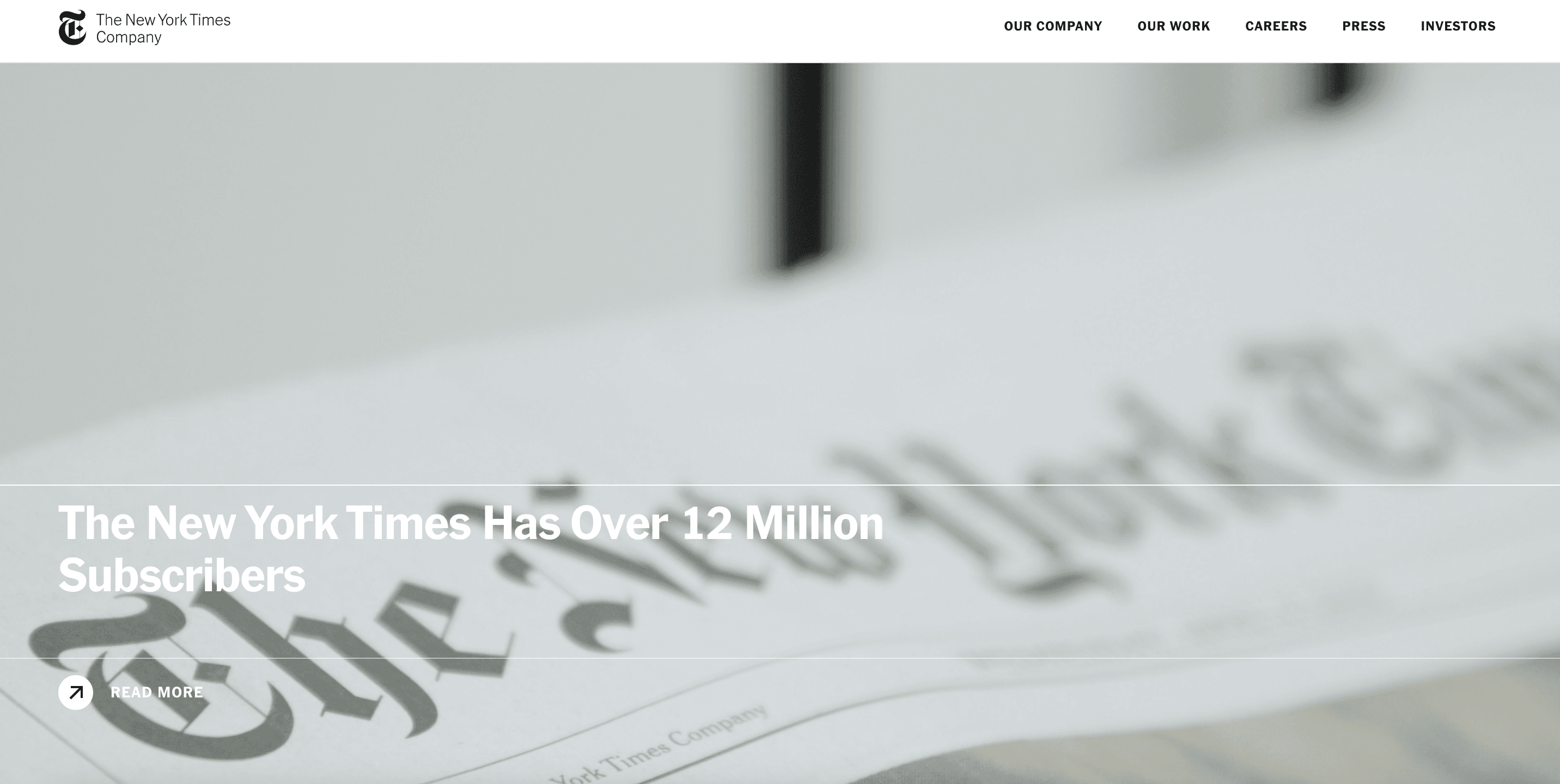
The New York Times Company(뉴욕 타임스 컴퍼니)는 1851년에 설립된 미국의 대표적 뉴스 기관으로, 깊이 있는 보도와 엄격한 저널리즘으로 잘 알려져 있습니다. 이 브랜드의 핵심 폰트 시스템은 Franklin Gothic과 Cheltenham입니다.
그중에서도 Franklin Gothic은 현대적이고 이성적인 느낌이 강한 서체로, 제목과 내비게이션, 다양한 디지털 인터페이스에 폭넓게 쓰입니다. 또렷한 형태 덕분에 단단하고 신뢰감 있는 시각적 이미지를 만들어 주며, 뉴욕타임스 브랜드의 전문성을 안정적으로 뒷받침합니다.
Cheltenham은 대비가 뚜렷한 세리프 구조와 조금 촘촘한 리듬감 덕분에 브랜드에 더 엄숙하고 전통적인 분위기를 더해 줍니다. 이 서체가 들어가면 전체적인 인상이 한층 단단해지고, 뉴스 매체가 지닌 특유의 힘과 역사적 깊이가 자연스럽게 드러납니다.
디지털 환경으로 무게중심이 옮겨간 지금도 뉴욕 타임스는 이 고전적인 서체 조합을 기본으로 유지합니다. 대신 더 가벼운 굵기와 넉넉한 여백을 적극 활용해 표현 방식을 현대적으로 조정하고 있습니다. 덕분에 오랜 시간 쌓아 온 브랜드 신뢰도는 그대로 지키면서도, 보다 명료하고 이성적인 시각 언어를 동시에 구현하고 있습니다.
블룸버그
BLOOMBERG
Font: Neue Haas Grotesk
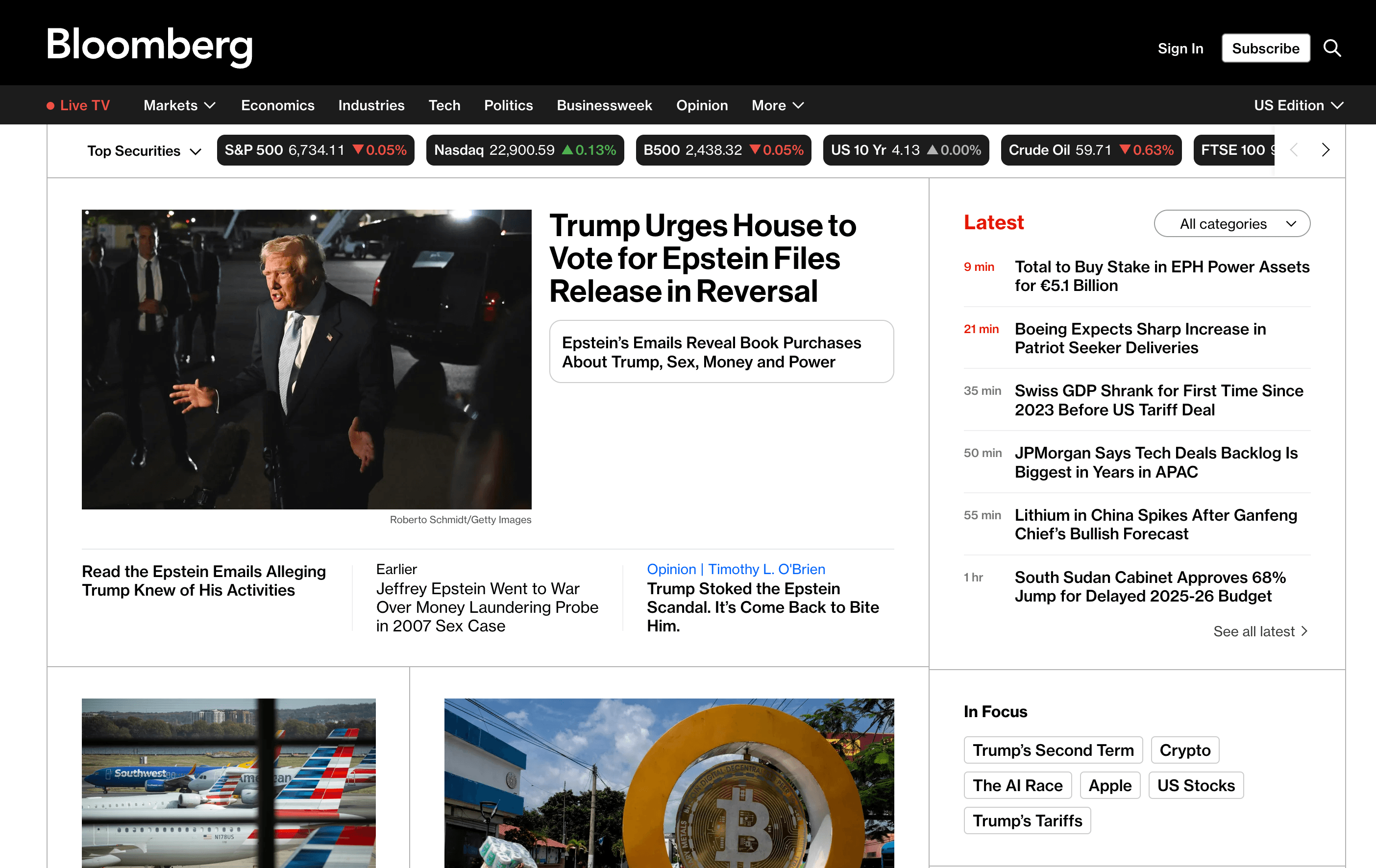
블룸버그는 세계에서 가장 영향력 있는 금융·비즈니스 정보 기관 가운데 하나로, 시각적 아이덴티티의 핵심 서체로 Neue Haas Grotesk를 사용합니다.
스위스 전통에서 출발한 이 산세리프 서체는 명료하고 엄격한 구조와 중립적인 기하학적 형태가 강점입니다. 덕분에 빽빽한 데이터, 차트, 금융 정보가 쏟아지는 환경에서도 높은 가독성과 전문성을 안정적으로 유지해 줍니다.
블룸버그의 디지털 플랫폼과 단말기 인터페이스, 브랜드 커뮤니케이션 전반에서 Neue Haas Grotesk는 균형 잡힌 굵기 체계와 군더더기 없는 글자 형태를 통해 차분하고 이성적이며 data-driven(데이터 드리븐)한 브랜드 이미지를 만듭니다. 기능성을 최우선에 두면서도 글로벌 금융 미디어로서의 효율성과 권위를 함께 강화하는 선택입니다.
워싱턴 포스트
THE WASHINGTON POST
Font: 커스텀 서체 Postoni + Franklin Gothic
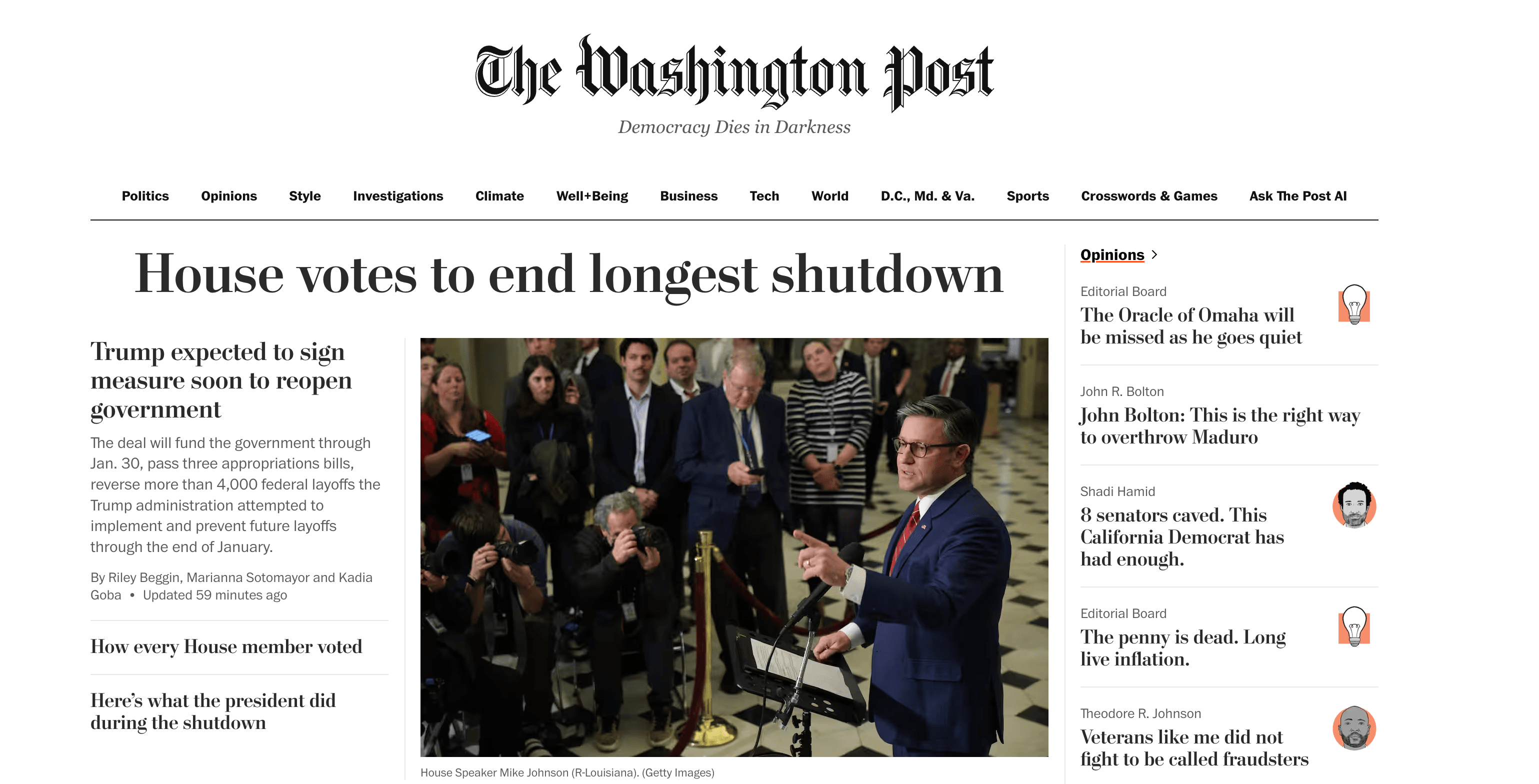
The Washington Post(워싱턴 포스트)는 1877년에 창간된 미국의 대표 일간지로, 심층 탐사보도와 정치 보도로 명성이 높습니다. 이 매체의 시각적 아이덴티티는 Postoni와 Franklin Gothic을 중심으로 구성되어 있습니다.
Postoni는 워싱턴 포스트를 위해 특별 제작된 세리프 서체로, 전설적인 서체 디자이너 Matthew Carter(매튜 카터)가 Bodoni의 고전적 구조를 현대적으로 재해석해 완성한 서체입니다. 헤드라인에서 우아한 권위와 묵직한 역사성을 드러내며, 신문의 정체성을 상징하는 핵심 요소로 작동합니다.
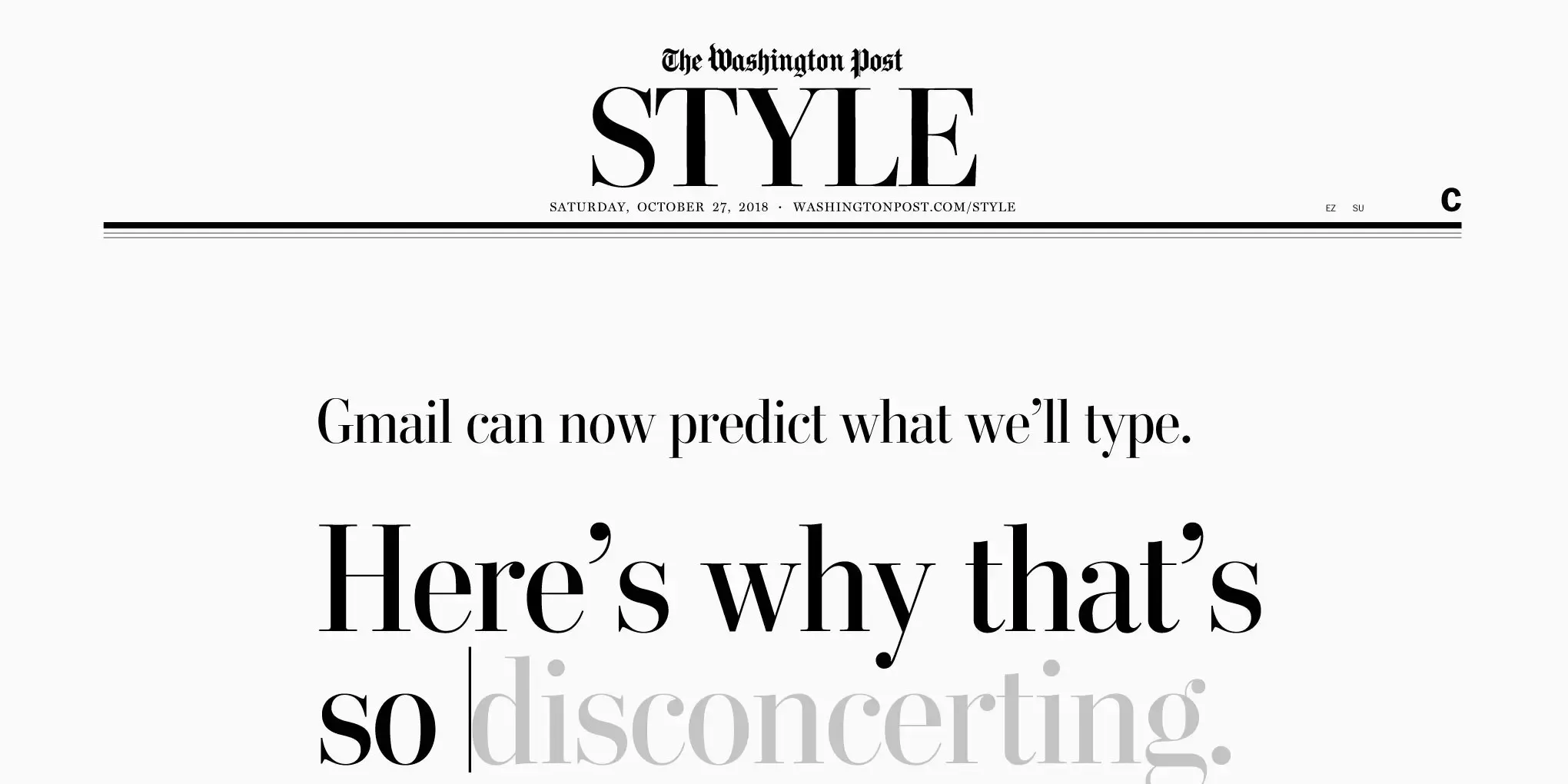
이에 반해 Franklin Gothic은 현대 뉴스 매체가 요구하는 명료함과 전문성을 더해 주고, 전체 시각 흐름에 선명한 리듬을 만들어 줍니다.
두 서체의 조합은 전통 신문이 가진 엄숙함을 유지하면서도, 디지털 시대에 맞는 이성적 긴장감과 역동성을 함께 보여 줍니다. 역사적 유산과 동시대적 감각을 자연스럽게 아우르는 시각 언어라고 할 수 있습니다.
POLITICO
Font: DIN + Helvetica Neue
POLITICO는 2007년에 설립된 워싱턴 D.C. 기반의 정치 뉴스 미디어로, 미국과 유럽의 정치 보도, 정책 분석, 선거 관련 뉴스를 중심으로 다루는 매체입니다.
브랜드의 시각적 아이덴티티는 DIN과 Helvetica Neue를 중심으로 구성됩니다. DIN은 기하학적 비례와 넓은 자형, 뛰어난 가독성을 강점으로 삼아 대제목에 주로 사용되며, 현대적이면서도 전문적인 인상을 줍니다. 반면 Helvetica Neue는 내비게이션과 본문에 활용되며, 간결하고 중립적인 특성 덕분에 전체 콘텐츠의 가독성과 일관성을 높여 줍니다.
이 두 서체의 조합을 통해 POLITICO는 디지털과 인쇄 환경 모두에서 이성적이고 권위 있으면서도 현대적인 뉴스 브랜드 이미지를 안정적으로 유지하고 있습니다.
BuzzFeed
BUZZFEED
Font: Proxima Nova
BuzzFeed는 2006년에 뉴욕에서 설립된 글로벌 뉴스·엔터테인먼트 미디어로, 디지털 콘텐츠 제작과 소셜 미디어 확산에 강점을 지닌 대표적인 인터넷 네이티브 매체입니다. 뉴스 보도와 트렌드 이슈, 인터랙티브 콘텐츠를 핵심으로 성장하며, 온라인 환경에서 자란 세대를 상징하는 브랜드로 자리 잡았습니다.
BuzzFeed의 시각적 아이덴티티에서 Proxima Nova는 핵심 서체로 사용됩니다. 서체 디자이너 Mark Simonson(마크 사이먼슨)이 디자인한 이 산세리프 서체는 기하학적 구조가 주는 이성적 느낌과 인문주의 서체 특유의 부드러운 감성을 함께 갖추고 있어, 현대적이면서도 친근한 인상을 전달합니다.
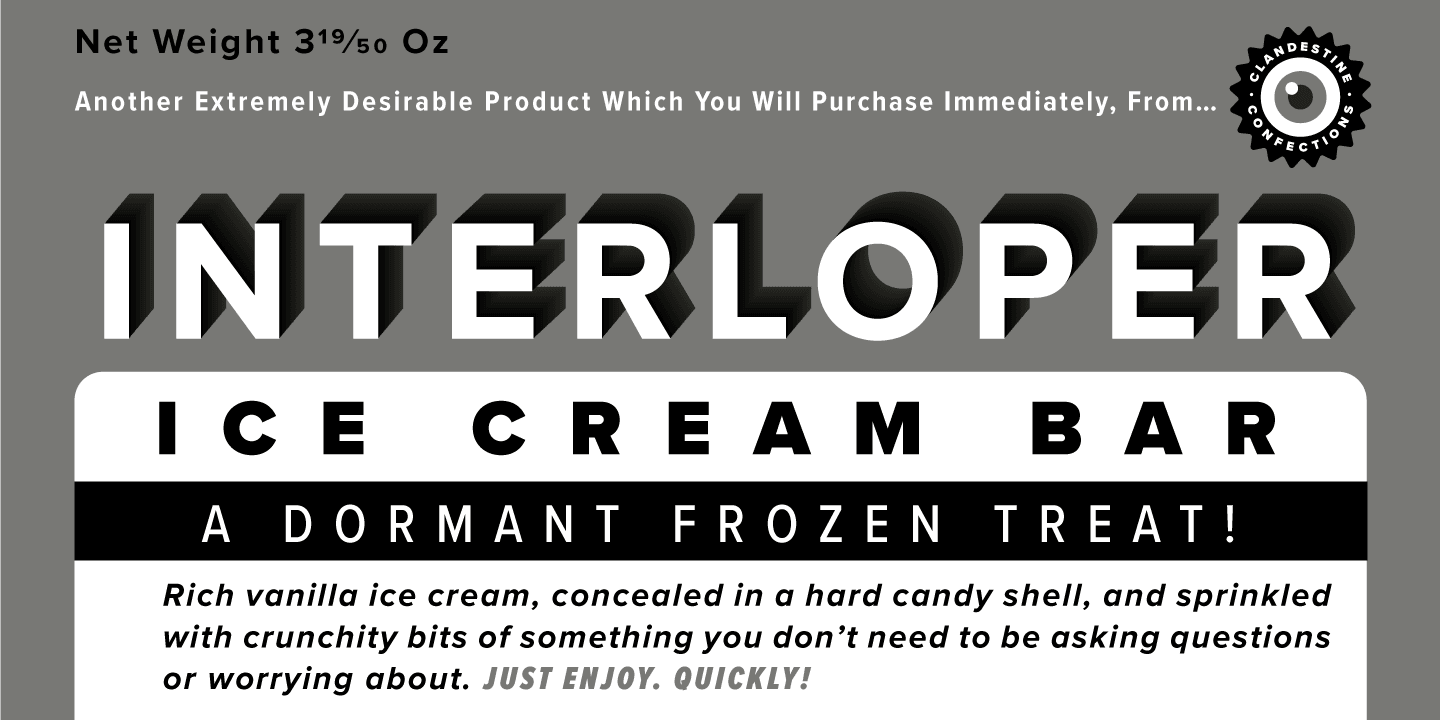
둥근 획과 균형 잡힌 자간 덕분에 Proxima Nova는 BuzzFeed 인터페이스를 가볍고 개방적이며 편안하게 보이도록 만듭니다. 이는 BuzzFeed가 지향하는 ‘디지털 네이티브, 즉각적인 콘텐츠, 빠르게 확산되는 커뮤니케이션’이라는 브랜드 성격과 자연스럽게 맞아떨어집니다.
타임스
THE TIMES
Font: Times New Roman 기반 커스텀 서체
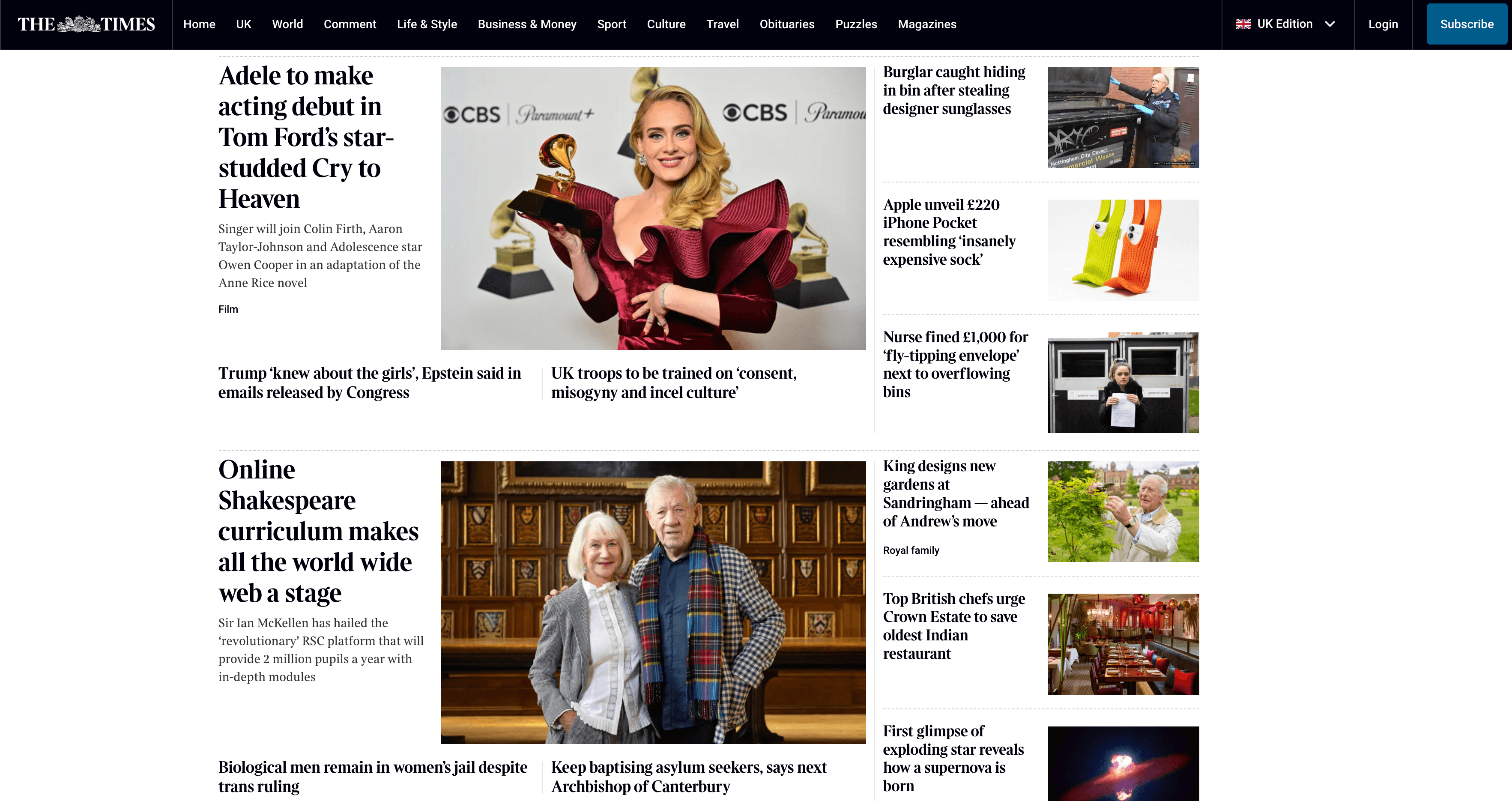
The Times(타임스)는 1785년에 창간된 영국의 대표 전국지로, 깊이 있는 보도와 권위 있는 논평, 전통적인 영국적 기풍으로 잘 알려져 있습니다.
브랜드 폰트 시스템은 클래식 서체 Times New Roman을 수정한 커스텀 서체 Times Modern을 중심으로 구성됩니다. 원본이 주는 책면 같은 묵직한 느낌과 달리, Times Modern은 더 가는 획 대비와 높은 명암, 넓어진 글자 폭을 통해 인쇄와 디지털 환경 모두에서 한층 가볍고 선명한 읽기 경험을 제공합니다.
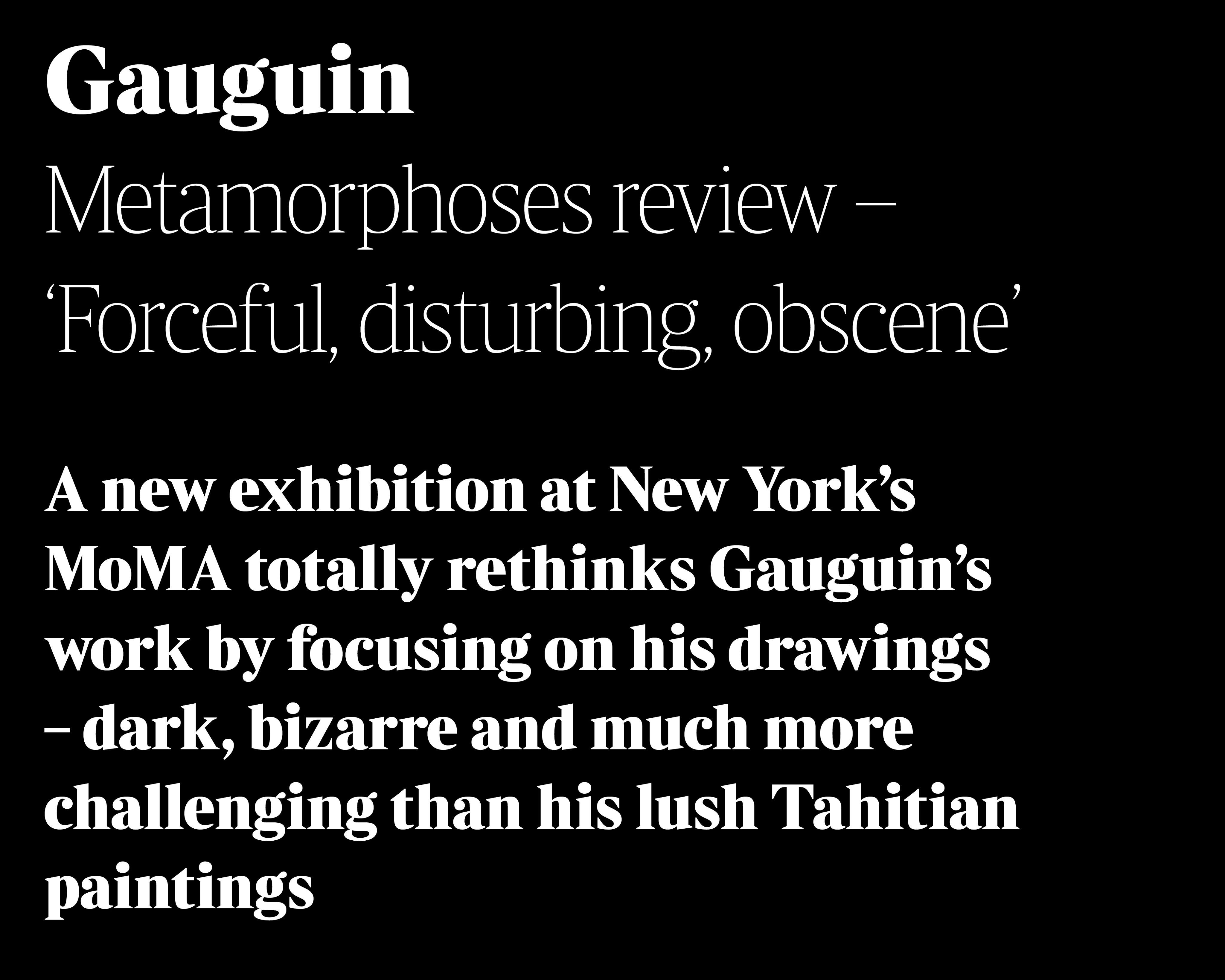
기존 서체를 현대적으로 다듬은 이 최적화 작업 덕분에 타임스는 영국식 신문 특유의 우아함을 유지하면서도 더 날렵하고 현재적인 표현을 구현합니다. 그 결과 디지털 시대에도 변함없는 중후함과 높은 인지성을 안정적으로 이어가고 있습니다.
허스트 매거진(그룹)
HEARST MAGAZINES
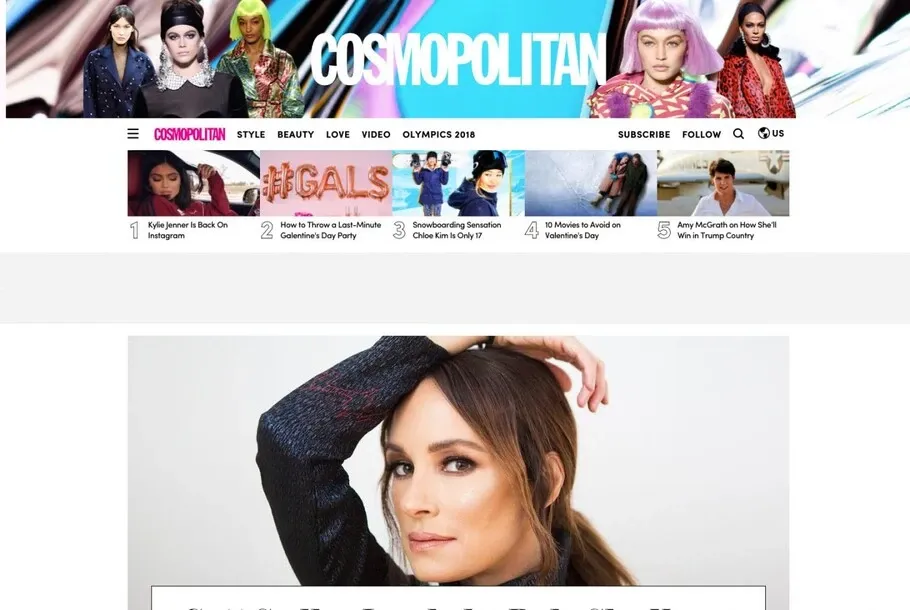
허스트 매거진 그룹은 지난 10여 년 동안 디지털 환경에 빠르게 적응해 왔습니다. 그 과정에서 Monotype(모노타입)과 긴밀히 협력하며, 각 브랜드의 온라인에서의 콘텐츠 가독성을 꾸준히 개선해 왔습니다.
브랜드 아이덴티티를 만드는 핵심 요소는 폰트와 컬러인데, Monotype의 폰트 관리 플랫폼인 Monotype Fonts는 매우 다양한 서체와 유연한 라이선스를 제공합니다. 덕분에 디자인팀은 여러 스타일을 부담 없이 시험해 볼 수 있고, 중요한 콘텐츠를 더 세련되고 정교한 시각 경험으로 표현할 수 있습니다.
또한 여러 플랫폼에서 운영되는 환경에서는 채널마다 스타일을 조금씩 달리해야 하지만, 폰트를 중심으로 전체적인 시각적 통일성은 유지할 수 있습니다. 이런 방식으로 허스트 매거진 그룹은 브랜드가 가진 전통을 지키면서도, 디지털 시대가 요구하는 빠른 속도와 유연함, 창의성을 자연스럽게 받아들이고 있습니다.
중국국제电视台
CGTN
Font: DIN
China Global Television Network(CGTN, 중국국제电视台)은 2016년에 설립된 국제 뉴스 플랫폼으로, 중국 중앙방송(CCTV)이 전 세계를 대상으로 운영하고 있습니다. 국제적 관점에서 중국의 이야기를 전하는 데 집중하는 매체입니다.
CGTN의 비주얼 시스템은 현대적이고 이성적이며 국제적인 이미지에 초점을 맞추고, 전체 디자인을 간결하지만 힘 있게 구성하고 있습니다. 브랜드 아이덴티티와 프로그램 패키지 전반에서 DIN 폰트를 적극 활용해 자막, 타이틀, 인터페이스 레이아웃을 통일된 톤으로 표현합니다.
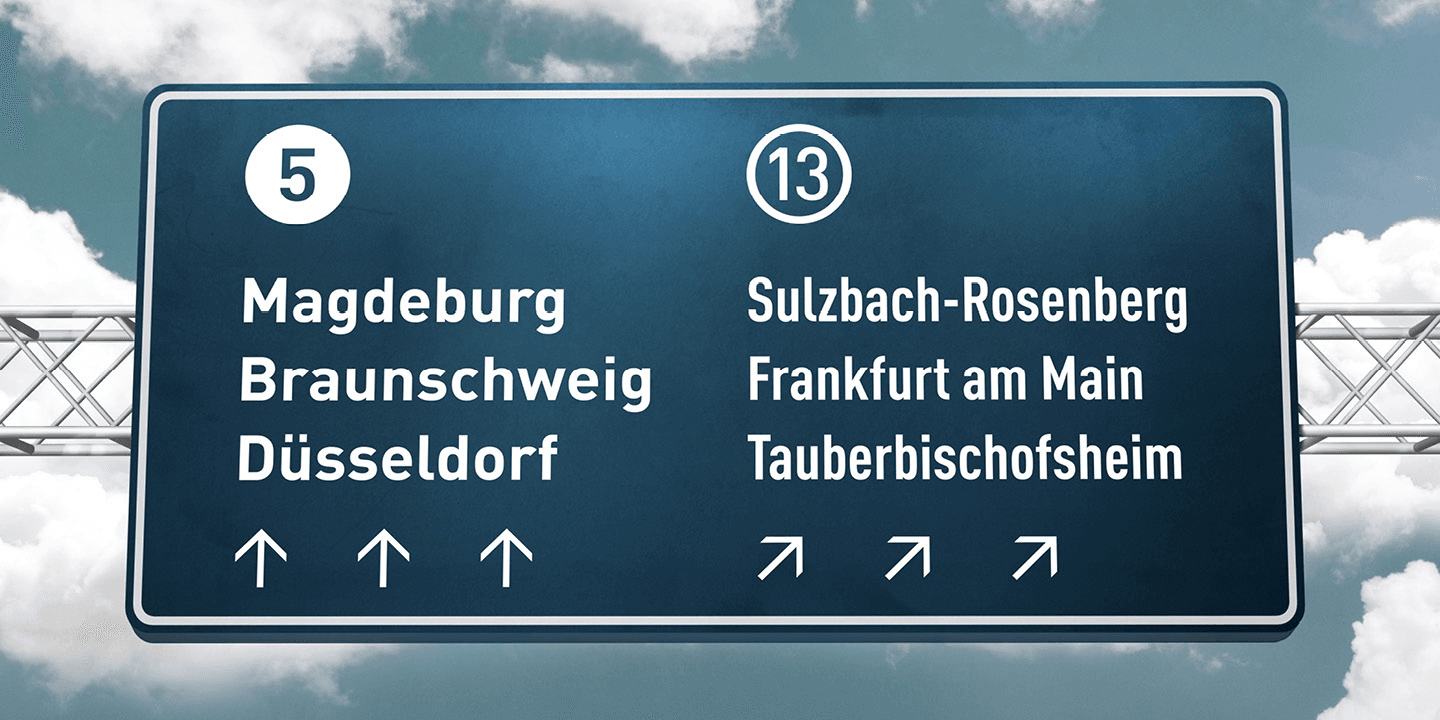
20세기 초 독일 산업 표준에서 비롯된 산세리프 서체 DIN은 기하학적으로 정확한 비례, 또렷한 획, 높은 가독성이 특징입니다. 덕분에 CGTN은 정보 전달에 최적화된 명료함과 전문성, 그리고 기술적이고 국제적인 분위기를 자연스럽게 구축했습니다. 이는 글로벌 뉴스 미디어가 요구하는 정확한 정보 전달력은 물론, 브랜드가 추구하는 ‘이성적인 표현’과 ‘국제적 커뮤니케이션’ 방향성을 잘 보여 줍니다.
정보가 넘쳐 흐르고 소식이 순식간에 퍼지는 지금, 폰트는 더 이상 글자를 담는 도구에 그치지 않습니다. 뉴스 미디어가 어떤 성격을 가지고 있는지, 얼마나 신뢰할 만한지 보여 주는 중요한 표시가 되고 있습니다. 뉴욕 타임스의 차분하고 이성적인 느낌, 타임스가 전하는 영국식 우아함, BuzzFeed의 가볍고 친근한 분위기까지 각기 다른 폰트는 우리가 뉴스를 어떻게 받아들이는지에 영향을 주고 있습니다.
종이에서 스크린으로, 인쇄에서 디지털로 시대가 바뀌어도 뉴스의 ‘목소리’는 서체를 통해 계속 이어집니다. 이 여러 목소리가 모여 만들어 내는 것은 전 세계 미디어가 공유하는 시각적 언어의 흐름이자, 문자와 신뢰, 시대를 둘러싼 끝없는 대화라고 할 수 있습니다.